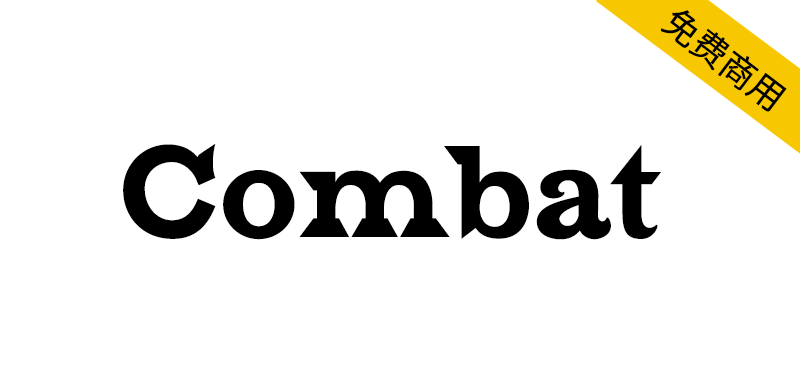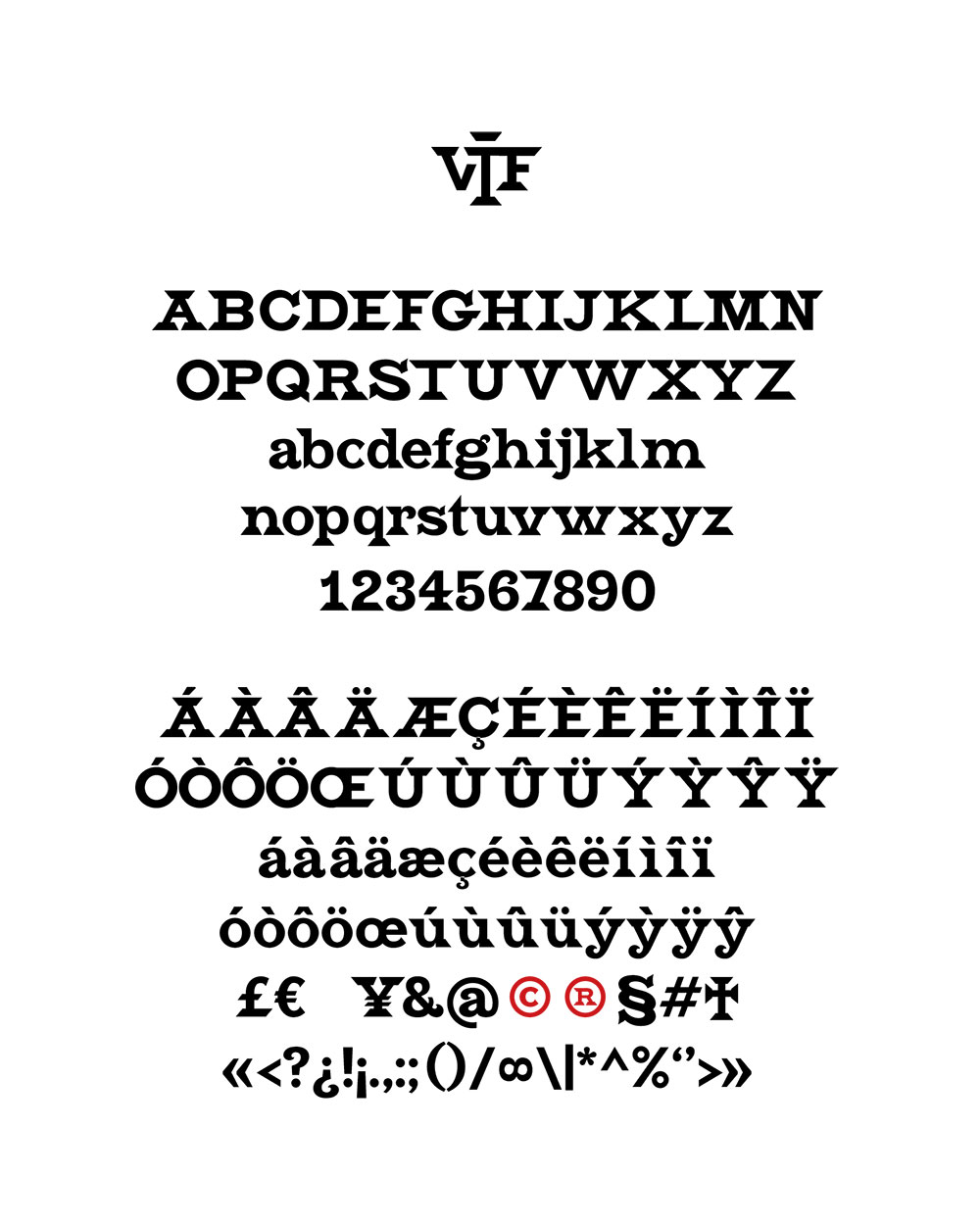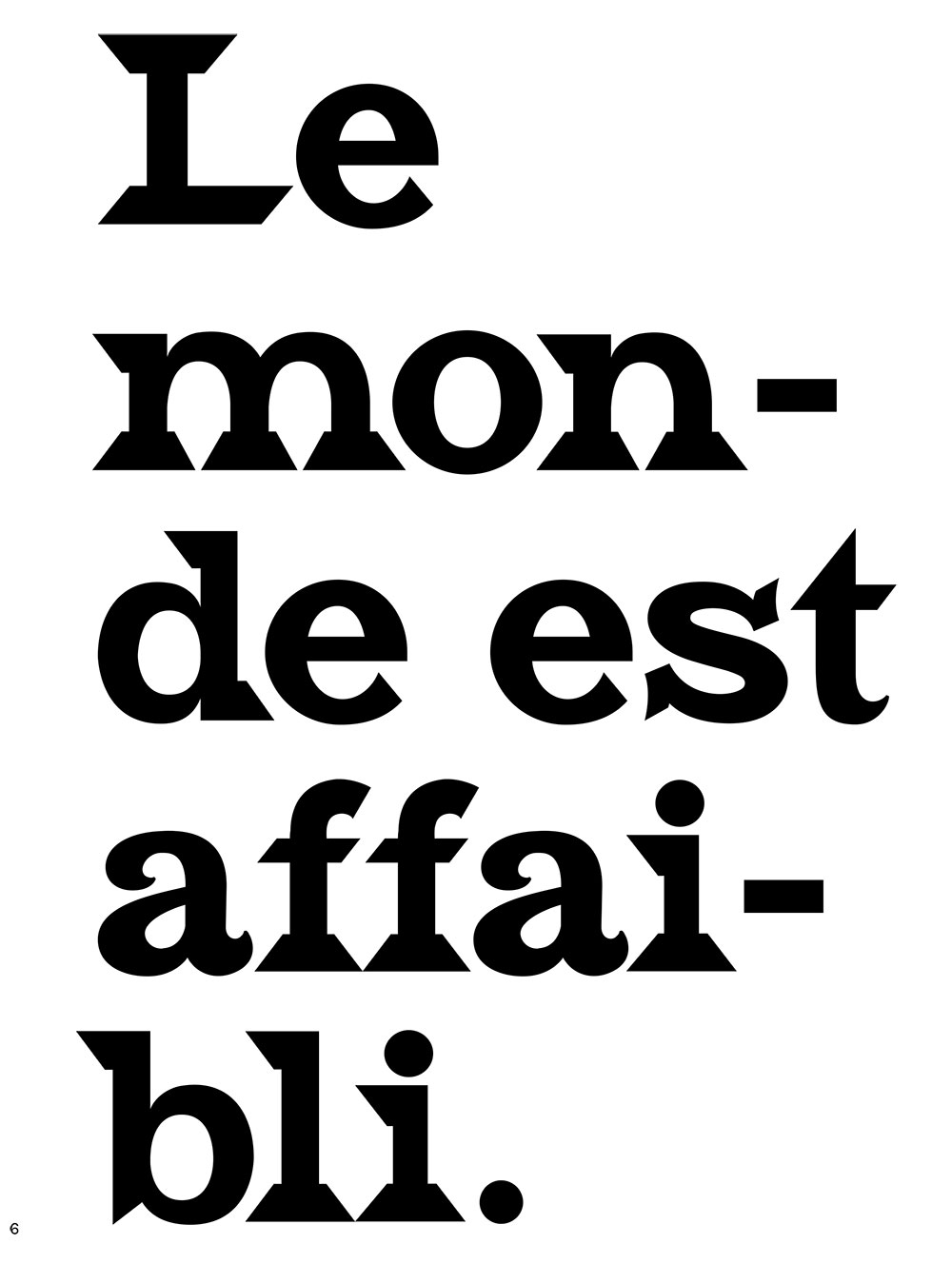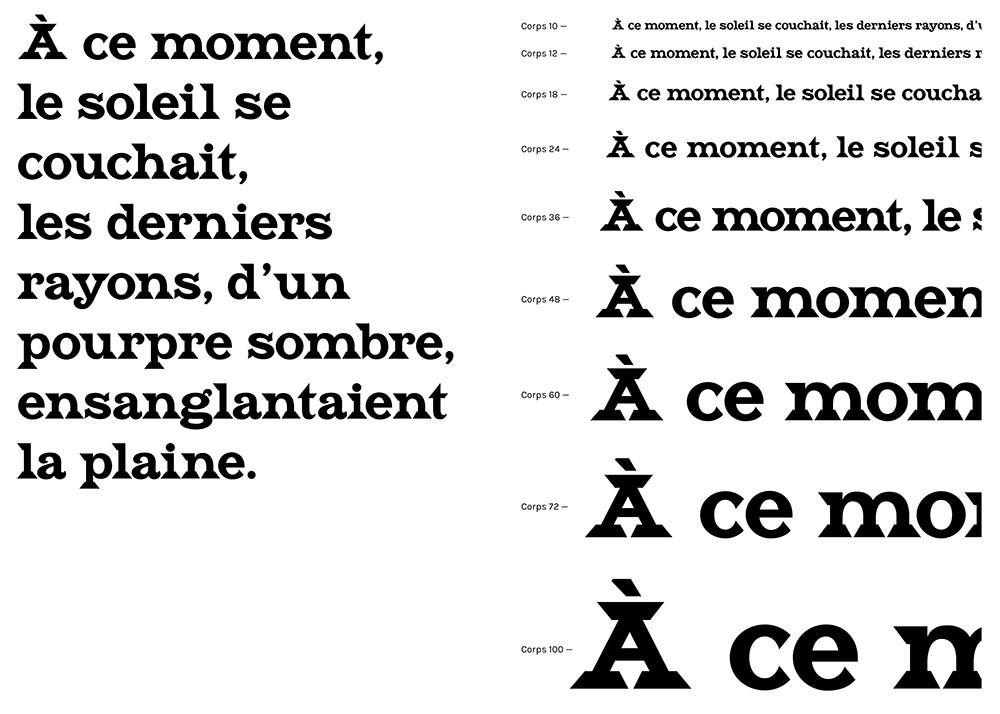
Combat是一种拉丁古董字体,衬线很强。它来自二十世纪初在法国利摩日出版的一份无政府主义报纸,名为《LE COMBAT SOCIAL》,标题中只有10个字母是为印刷而创建的,100年后,这种字形被单独做成了一种字体。
Combat is a latin antique typeface with strong serifs. It comes from an early XXth century anarchist newspaper published in Limoges, France, called LE COMBAT SOCIAL. Only the 10 letters of the title were created for printing. 100 years later, the font exists on its own.